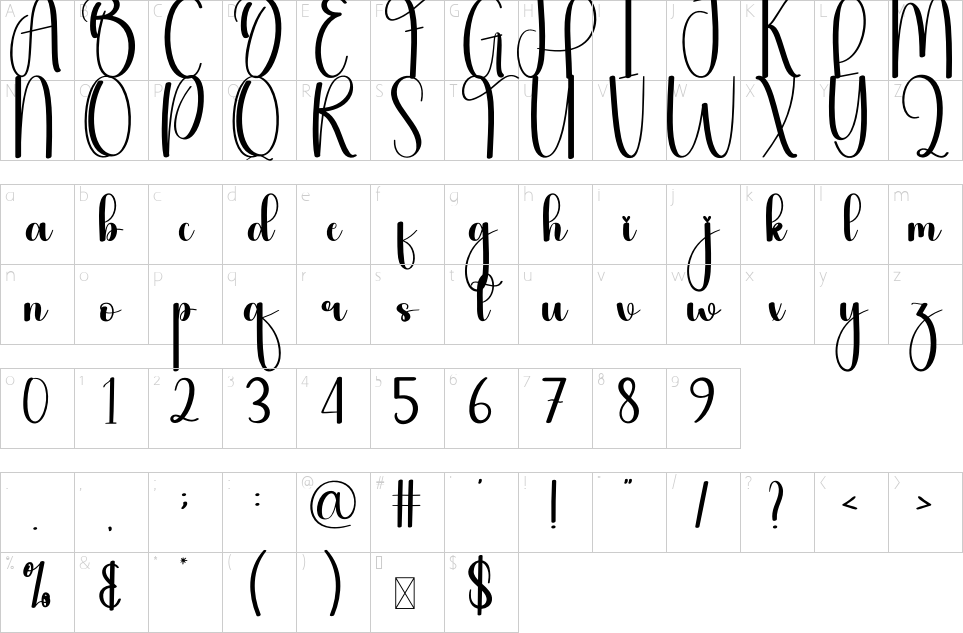
A Graduation Font é uma elegante escolha para designers que desejam adicionar um toque sofisticado às suas criações digitais. Desenvolvida por William Jhordy, esta fonte foi criada especialmente para quem busca o charme dagraduação em sua próxima peça de trabalho. Com seu design minimalista e elegante, a Graduation Font é perfeita para nomes, datas importantes ou qualquer outra informação que mereça um ar de importância. Disponível tanto no sistema operacional Windows quanto Mac, esta fonte se destaca por sua facilidade de uso e a capacidade de personalização. Com apenas um clique, você pode transformar uma simples mensagem em um texto cheio de estilo, ideal para sites, aplicativos ou documentos importantes. Esta fonte é gratuita e sem restrições, permitindo-lhe explorar todas as suas possibilidades sem custos adicionais. E embora não tenha uma descrição mais detalhada do designer, a Graduation Font se torna um ótimo complemento para designers de todos os níveis, oferecendo praticidade e estilo em cada uso. Não perca essa oportunidade de dar um toque especial às suas criações digitais com a Graduation Font.